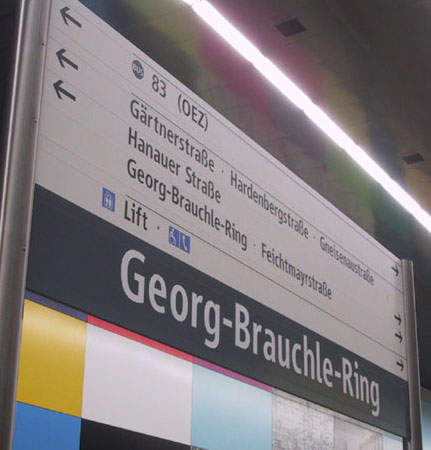
■■■Popular Fonts: フォント使用例 2■■■
最近人気のフォントの使用例です。是非、画面をクリックして大きな画像をご覧下さい!
メトロ駅標識:München  |
カレンダー:Rapp  |
チラシ:Tchibo  |
パンフレット:Festo Harmonices Mundi  |
■■■ What is it ?: 「Astrotype™」 フォントって? 3■■■
TakeType No. 5 のシンボル部門の中に収録している 「Astrotype™」 フォント。最近はよく雑誌の最終ページに星占いのページが載っていたり、新聞にも占いの項目があったり、TVでもカウントダウン的に星座占いがあったり、インターネット上でも占いのページがあったりと日常生活では既に占星術のフォントはよく使われていたんですね。
では何故「Astrotype™」 フォントを??
by Andreas Hild, 2002
「私が知っている天文学や占星術フォントのどれもが私が望んだものでなかったという事もあり、天文学や占星術のフォント研究を始めました。その後、徹底的に使えるフォントを研究し、天文学や占星術のフォントをデザインする必要があるのではと思い、挑戦することを決意しました。Adrian Frutiger 氏のすばらしい功績・3つのボリューム 「人類とその記号・符号」やプロフェッサー Friedrich Friedl 氏の記号・符号、筆記体活字 、シンボルや官印フォントなどは私が最も影響を受けたフォントです。
走り書きのような鉛筆や細かいラインの細かいデザイン技術などは Mac のアドビイラストレータでデザインしました。「Astrotype™」フォントは、天文学占星術の文学、本、新聞、雑誌などで使用するのに最適です。その際にテキスト内にグラフィックスを伴うとさらに有効にフォントを使用することができます。又、すべてのウエイトをうまく使用して挿入絵や例解などでポスターやタロットカードなとに使用するとさらなる可能性が広がります。
明瞭かつ均質でシンプルな「Astrotype™」 フォントはとてもユニークな印象を与えます。 書体はナチュラルで上品かつ他テキストへの統合もでき調和するので異なるウエイトを使用してのコンビネーションを組み合わせればさらに創造的な作品に仕上がります。例えば、「Astrotype™ P Dot」 フォントの上に「Astrotype™ N Dot」 フォントを置いて異なる色を使ってみると装飾物、アイコンやスクリーンのボタンなどに使用するのに最適です。」
■■■What is it ?: 「Seebad」 フォントって? 4■■■
デザイン by Silvan Kaeser, 2002
現在、好評発売中の 「Take Type No. 5」 の Display カテゴリー内に収録されています。
Silvan Kaesar デザインのSeedbad™フォントは、ジュネーブの湖付近沿いにあったユニークな道標文字を見た後にデザインされました。異なる4つのウエイトは、縁をカットした新しい最先端のスイススタイルの代表ともいえるデザインです。Seedbad™フォントは、幾何学的に構築されたフォームとnarrow をベースにデザインされているのが特徴です。又、いくつかのキャラクター、例えば下にある t の部分や g なども特徴があります。今後ちょっとしたスパイス(インパクト)が欲しい時には、このウルトラモダンなフォントのレイアウトをお勧めします。是非、あなたのフォントコレクションの1つにSeedbad™フォントを!!
↑↑↑Linotype Univers™ と Linotype Ziqibacks™ フォントも使用しています。